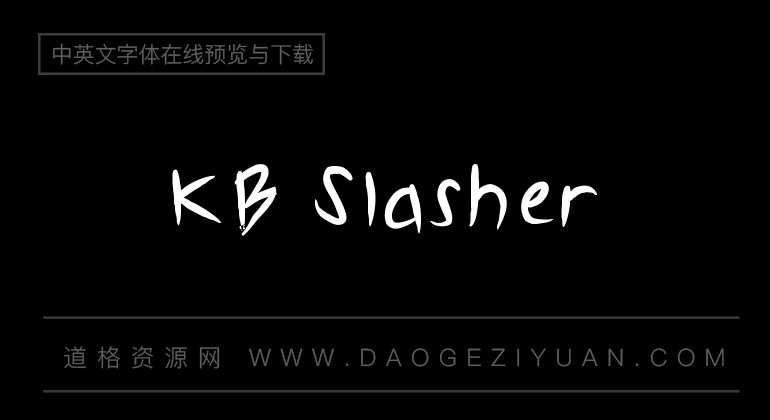
KB Slasher 是一种现代风格的商业字体,由设计师 Khairil Anwar 创作。这种字体具有创新和独特的外观和感觉,适合用于许多不同类型的设计项目。KB Slasher 的特点包括清晰的线条和尖锐的角度,让字母看起来非常锐利和现代化。此外,它还具有多种字重和字形,可根据不同设计需求进行选择。内容介绍
KB Slasher是一款非常不错的手写艺术字体,具有很好的视觉感,适合于文化类的宣传设计、商业类品牌的广告和产品包装设计以及个性化文字排版等较多场景。